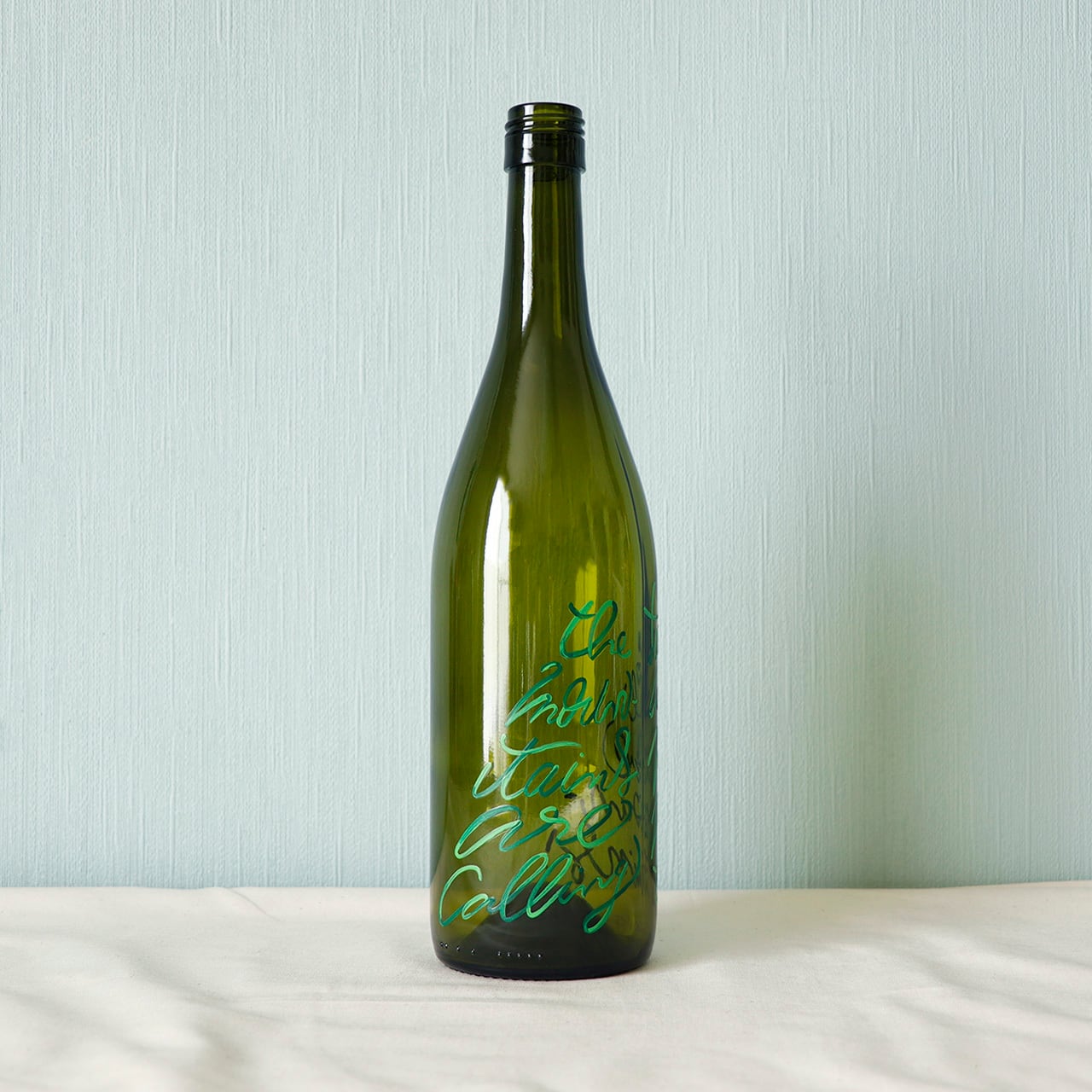
【BOTTLE PAINT ART】Mountain words 02
ワインボトルにペイントした、気軽に飾れるアートな作品が登場!
Faith will move mountains.
信念は山を動かす
The mountains are calling.
山が私を呼んでいる
言葉に合わせて、文字の形も山になっています!
こちらは文字がグラデーションになっています。
光が入るとこに置くと、瓶の色とともに文字も影になって素敵ですよ!!